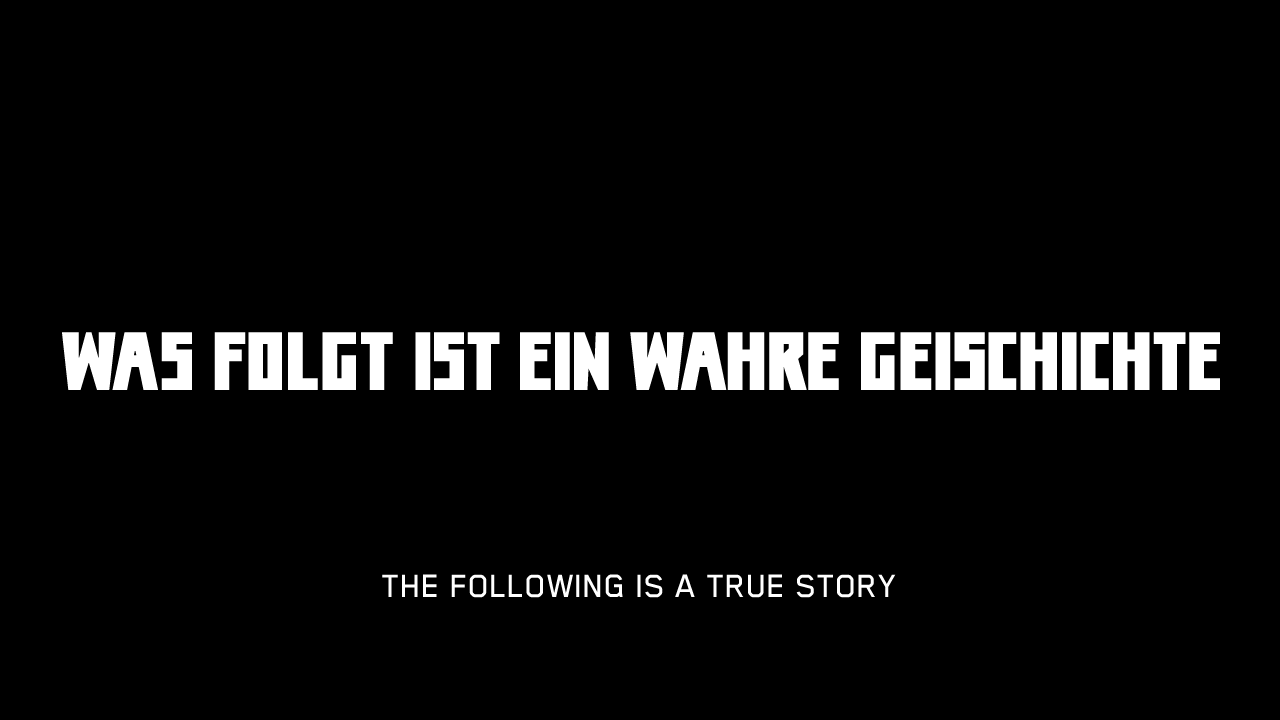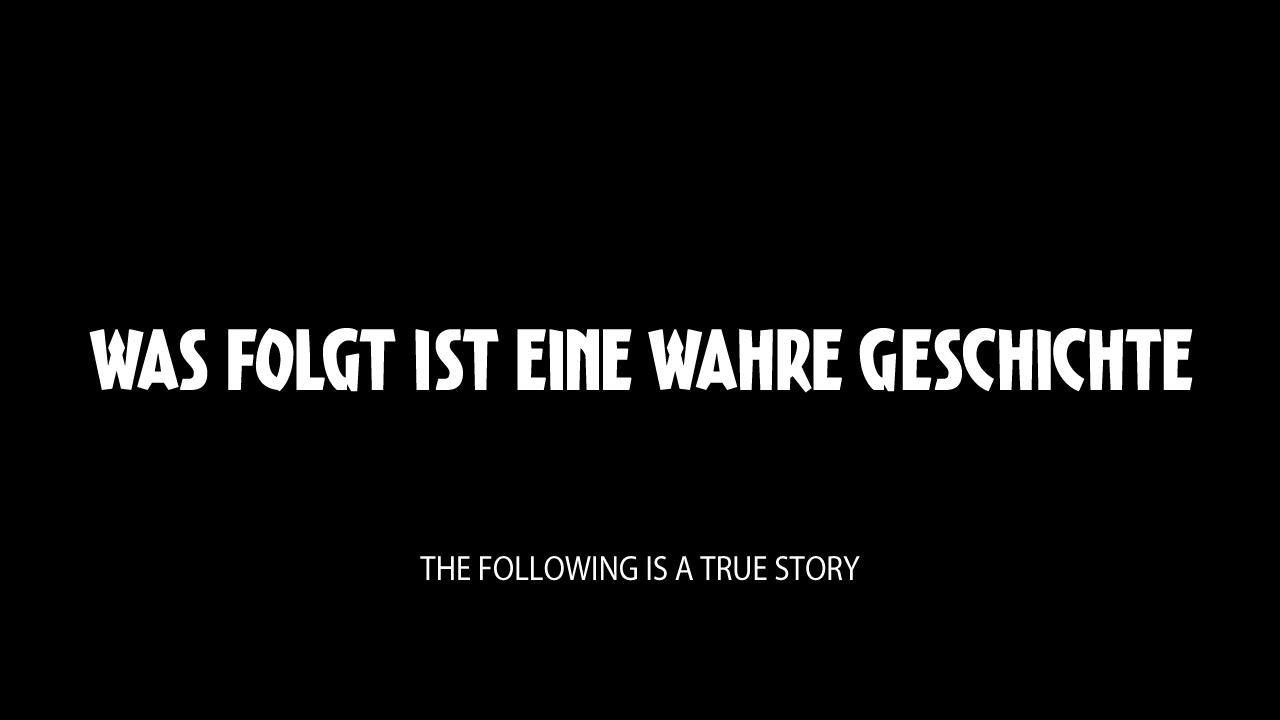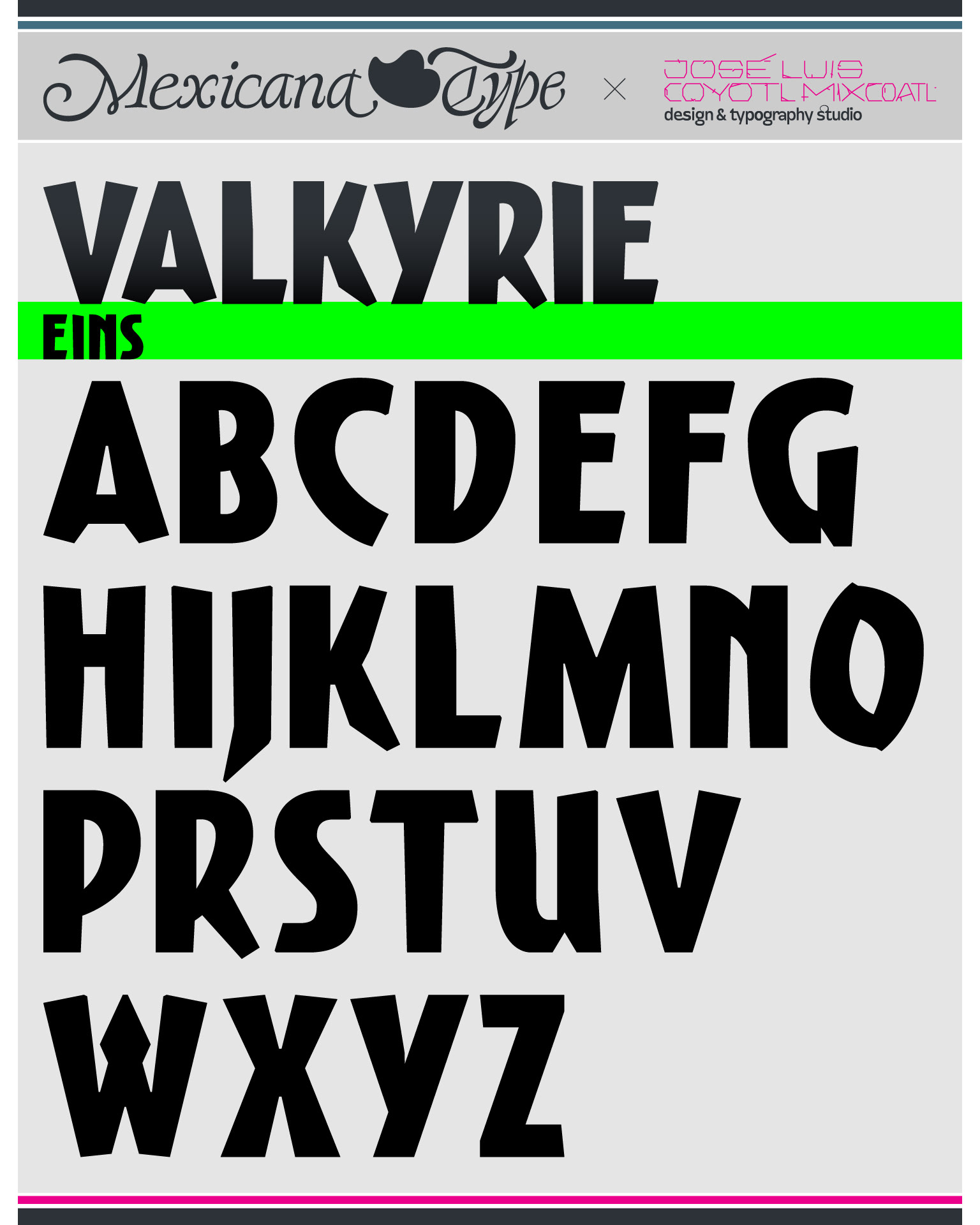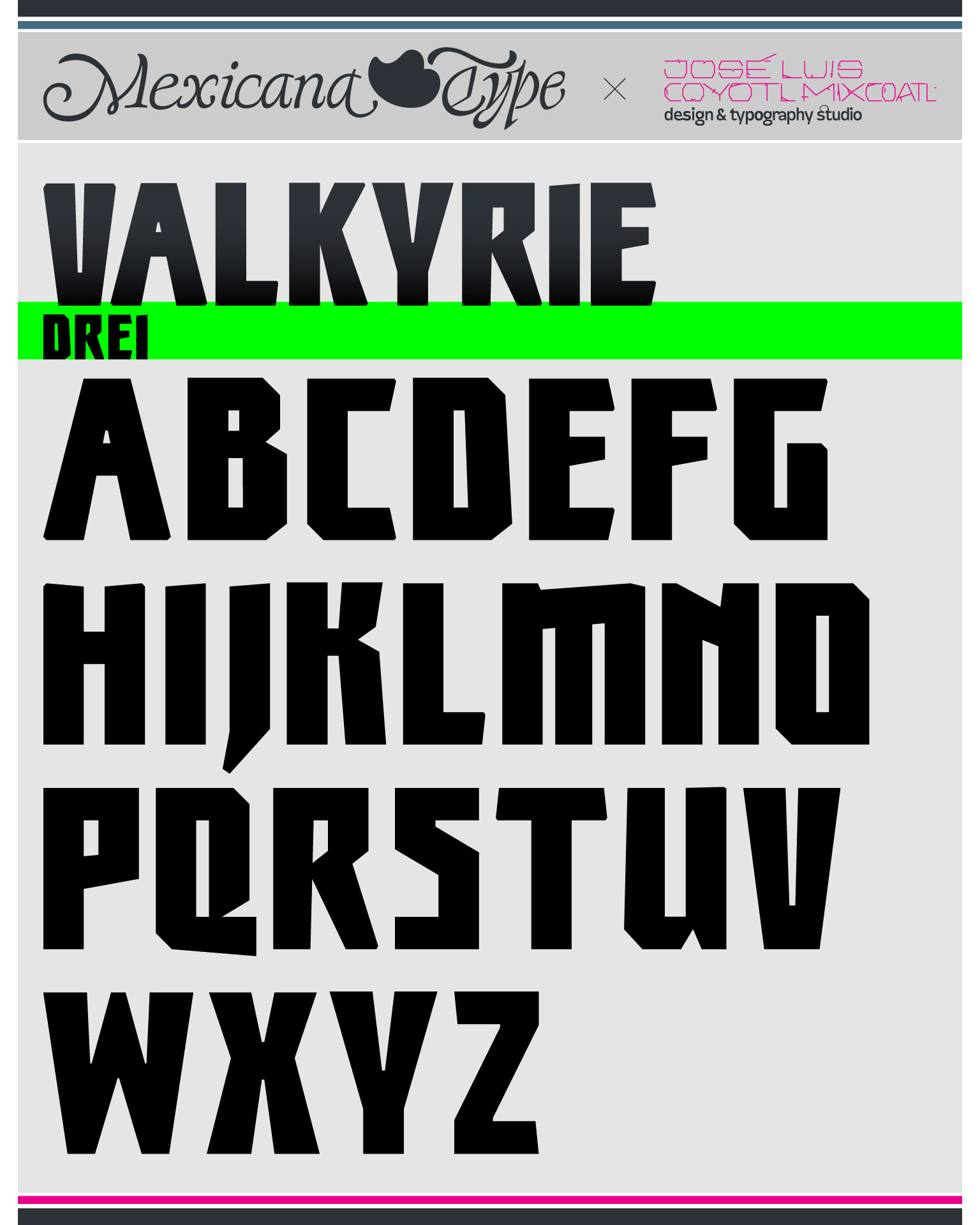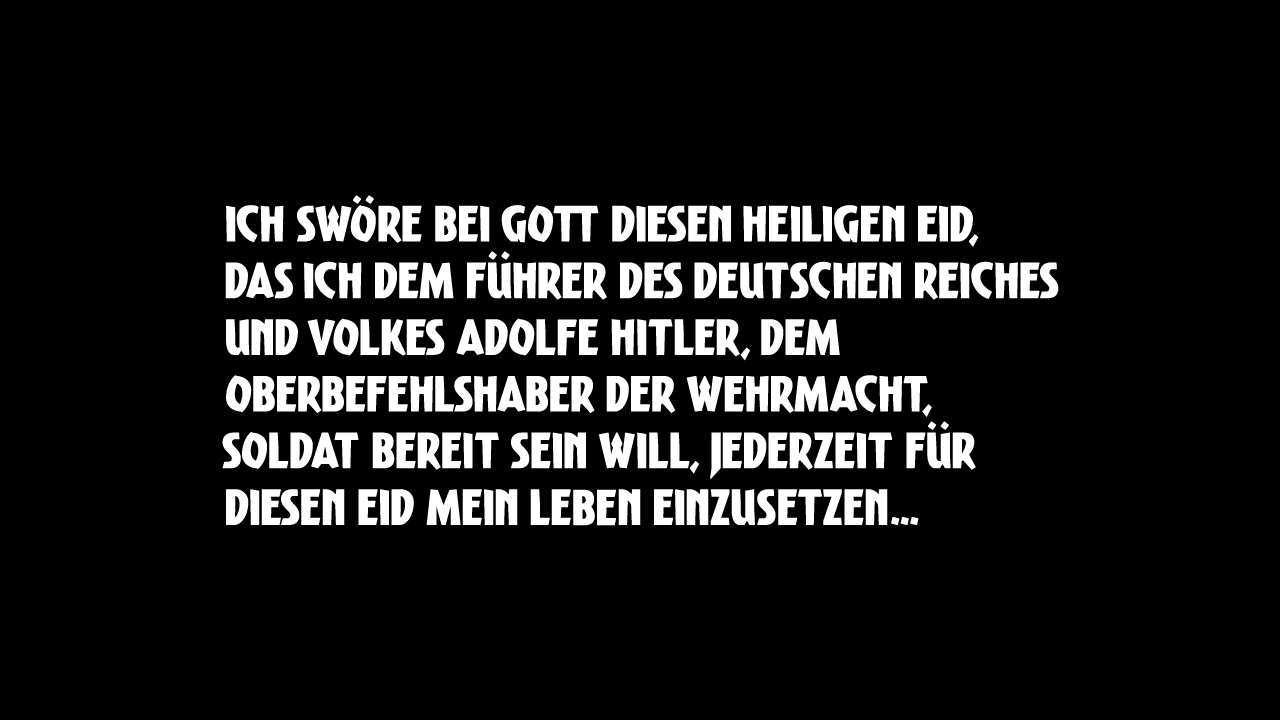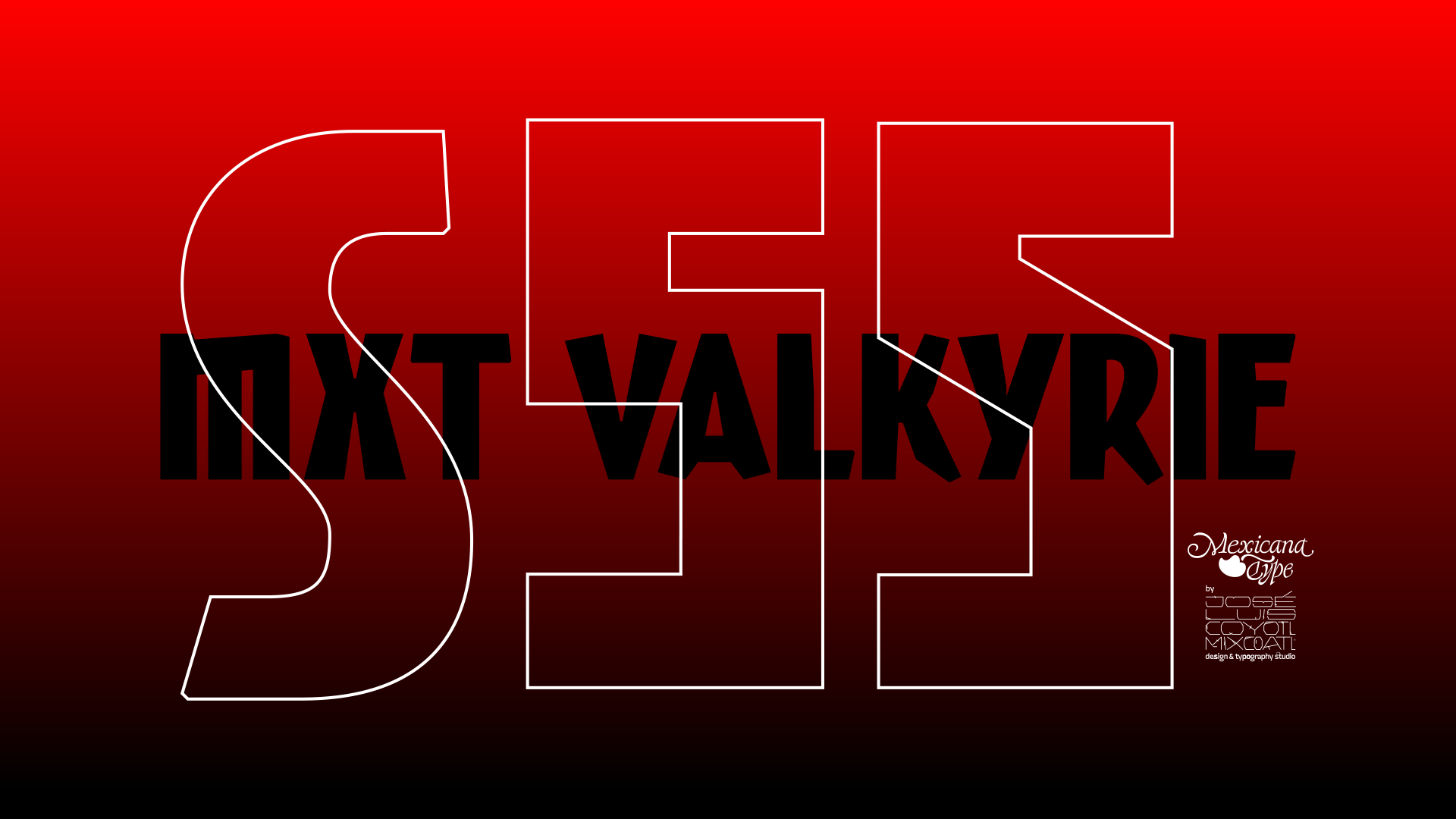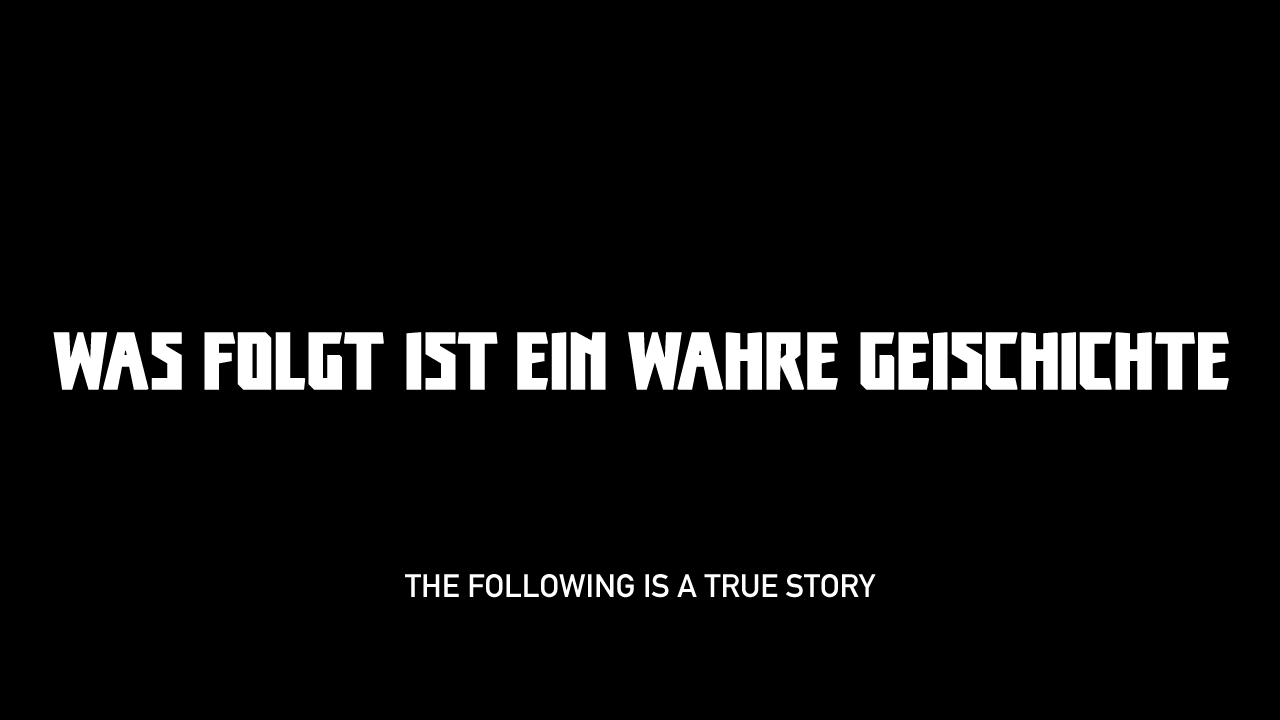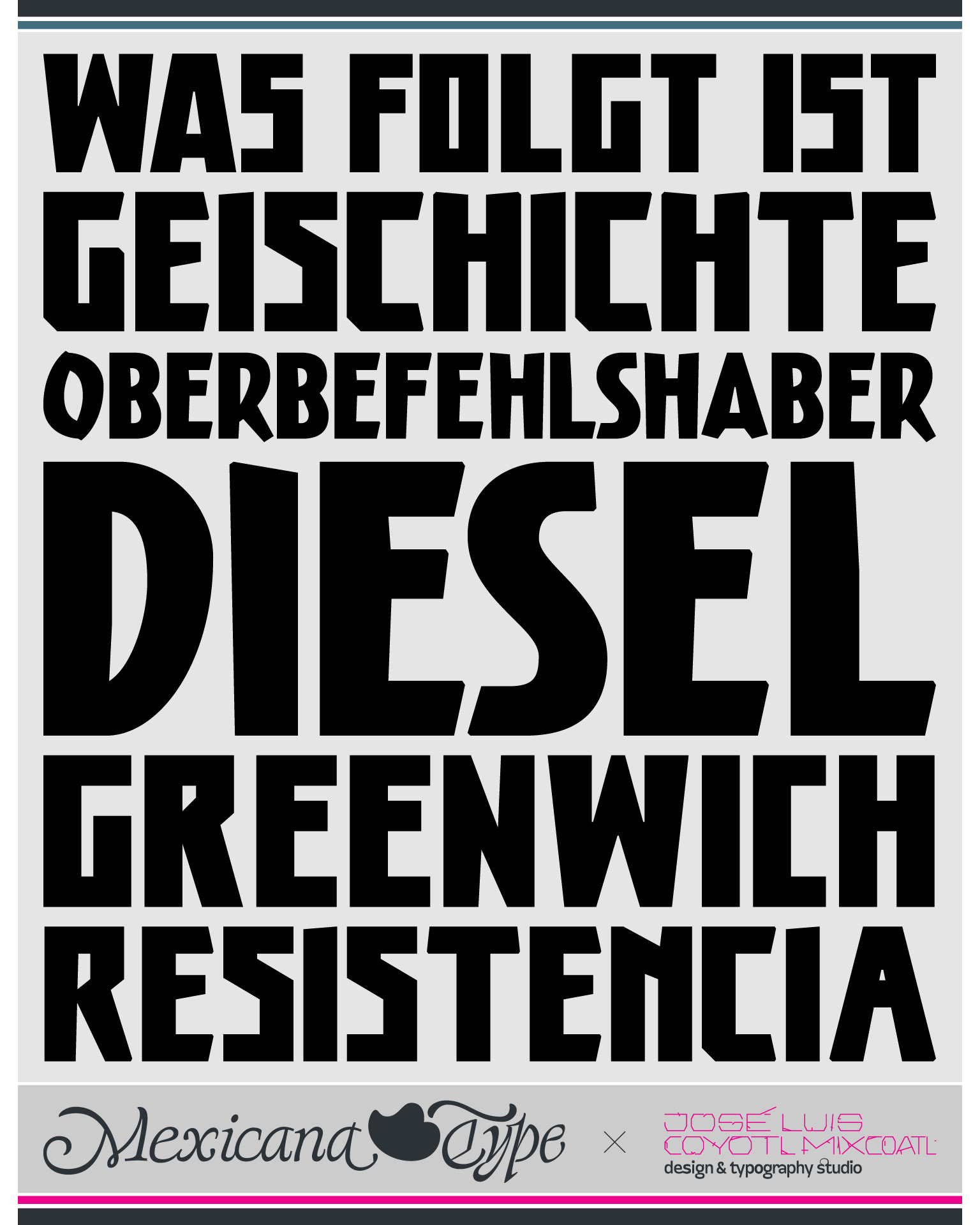
MxT Valkyrie fue un proyecto que inició como una exploración tipográfica para un proyecto de créditos de cine de la película del mismo nombre, 'Valkyrie' dirigida por Bryan Singer y estelarizada por Tom Cruise. La idea que estaba probando era recuperar una tipografía de origen alemán de la época en la Alemania de antes de medio siglo XX, que no fuera la clásica Gótica Fraktur, sino algo mucho más callejero y urbano, pues los textos de la secuencia de créditos incluía los textos en alemán y en inglés en su título principal y en descripciones.
En el proceso se encontro una serie de referencias que remitían a un estilo mucho más arquitectónico y escultural, de cuerpo más vertical y de mayúsculas modulares. De modo que se desarrollaron tres modelos, dos más cuadradas y otra de trazos mas fluídos. De modo que Se planteó el diseño bajo una perspectiva quizá un poco más contemporánea sin perder su naturaleza vernácula, además de cierto aire también de letras holandesas de la epoca que se emparentaban también con los estilos alemanes. Se desarrollaron unos pocos caracteres para probar sobre las pruebas de tipografía y si bien no se usaron en la versión final, resultaron en un ejemplo interesante del cual se pudieron completar un set de caracteres básicos en los tres estilos que pudiesen usarse también para otros proyectos.